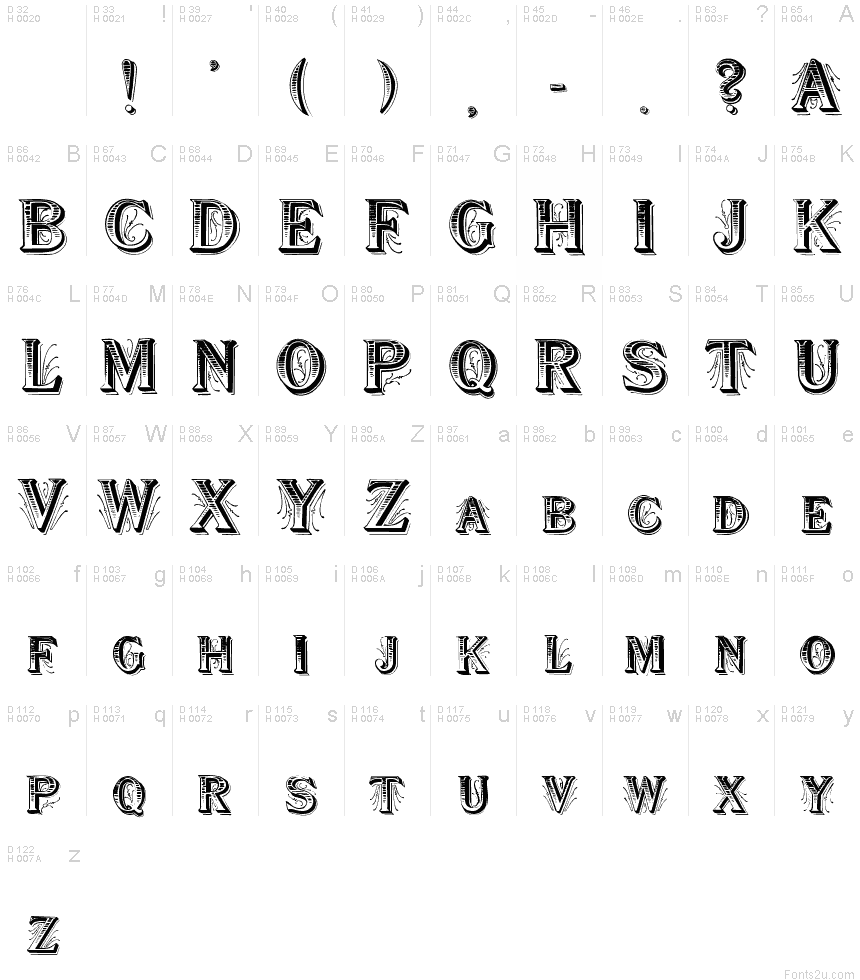
ShowBoat, di Brian Prince, è un font display gratuito in stile vittoriano (solo maiuscole), che evoca il fascino dei vecchi manifesti fluviali e dei programmi teatrali. Le lettere mescolano righe incise, svolazzi interni e grazie a cuneo, conferendo all'alfabeto un carattere teatrale piuttosto che puramente decorativo.
È ideale per titoli di manifesti, flyer di eventi, copertine di menu, cartellini, packaging di souvenir e monogrammi in cui un tocco di spettacolo del XIX secolo aiuta a creare l'atmosfera giusta. Come font gratuito, ShowBoat dà il meglio di sé in brevi sequenze: le sue maiuscole decorate hanno una presenza visiva tale da poter incorniciare un logo per un saloon, un'intestazione vaudeville o un titolo a tema fluviale senza bisogno di aggiungere altro.